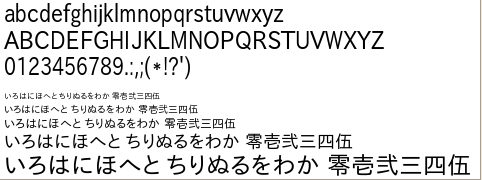
مونا (خط)
مونا هو خط ياباني متناسب ذو بكسل لنظام X Window ، مشتق من عائلة خطوط Shinonome النقطية، [ 1 ] وهو أيضًا خط TrueType . [ 2 ] يهدف إلى تمثيل رسومات Shift JIS الفنية بشكل صحيح، والتي تتطلب جميعها تقريبًا خط MS PGothic. سُمي مونا تيمنًا بشخصية مونا ، وهي تميمة حرفية لشركة 2channel .
يستخدم برنامج مونا رموزًا من خط شينونومي (東雲) الإصدار 0.9.9 (غوثيك) للصور النقطية المضمنة. في الإصدار 2.30-pre، كان البرنامج يستخدم خطوطًا خارجية من خط كوتشي-غوثيك. إلا أنه تم استبدالها بخط كوتشي البديل في الإصدار 2.30-pre2 بعد اكتشاف أن خط كوتشي ينتهك حقوق الطبع والنشر. بعد ذلك، أصبحت الرموز في مونا تُشبه تلك الموجودة في خط إم إس بي غوثيك.
يدعم برنامج Mona صفحات الترميز التالية: 1252 (اللاتينية 1)، 1250 (اللاتينية 2: أوروبا الشرقية)، 1251 ( السيريلية )، 1253 (اليونانية)، 932 (JIS/اليابان)، 737 (اليونانية؛ 437G سابقًا)، 437 (الولايات المتحدة).
مخطط مونا
يتضمن كود المصدر لحزمة خط مونا الإصدار 2.30pre2 من mona-outline، والذي يتألف من مجموعة فرعية من الرموز الموجودة في خط مونا. يدعم جدول تخطيط OpenType الوصلات القياسية في اللغة الافتراضية. عند عرض الخط باستخدام عارض خطوط ويندوز، يظهر خط أفقي فوق الرمز.
يدعم mona-outline صفحات الترميز التالية: 932 (JIS/اليابان)، 437 (الولايات المتحدة).
IPA monafont
IPA monafont هو امتداد لخط IPA ( IPAフォント) ، [ 2 ] خط Sazanami (さざなみフォント) ، [ 3 ] خط Mona (モナフォント) ، [ 4 ] M+ Fonts ( M+フォント) [ 5 ] تم إنشاؤها بواسطة Jun Kobayashi، والتي تتكون من عائلة من الخطوط:
- IPAMonaGothic ( IPA モナー ゴシック)
- IPAMonaMincho ( IPA モナー 明朝)
- IPAMonaPGothic ( IPA モナー P ゴシック)
- IPAMonaPMincho ( IPA モナー P 明朝)
- IPAMonaUIGothic ( IPA モナー UI ゴシック)
تدعم عائلة خطوط IPA monafont صفحات الترميز التالية: 1252 (اللاتينية 1)، 1251 (السيريلية)، 932 (JIS/اليابان)، 950 (Big-5)، مجموعة أحرف ماكنتوش (الأحرف الرومانية الأمريكية)، مجموعة أحرف Windows OEM، 866 (MS-DOS الروسية)، 865 (MS-DOS الإسكندنافية)، 863 (MS-DOS الفرنسية الكندية)، 861 (MS-DOS الأيسلندية)، 860 (MS-DOS البرتغالية)، 855 (IBM السيريلية؛ الروسية الأساسية)، 437 (الولايات المتحدة).
أُعيد تصميم رموز الأحرف الصينية واليابانية والكورية لتشبه خط Arial Unicode MS ، بينما أُعيد تحديد موضع الرموز الفرعية لهذه الأحرف وتغيير حجمها. وكما هو الحال في عائلتي خطي MS Gothic وMS Mincho، يستخدم رمز الين المعكوس بدلاً من الشرطة المائلة العكسية. ويمكن إيجاد استبدال غير قياسي مماثل في عائلتي خطي Gulim وDotum.
ملاحظة: بعض الرموز التي تمثل أحرفًا غير مسافات بيضاء تكون فارغة.